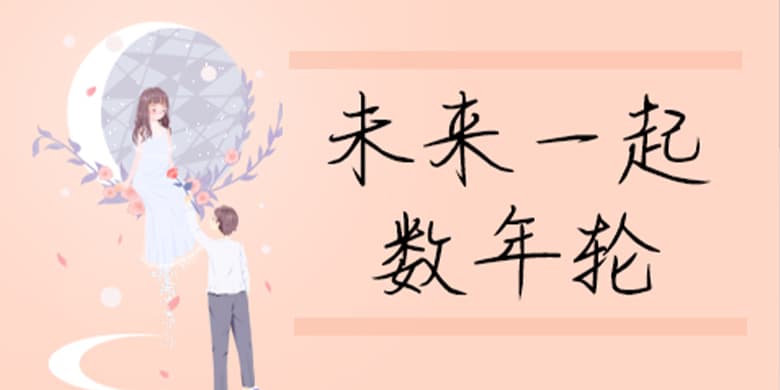
品牌:方正手迹设计师:王航发行时间:2020字库编码:简繁扩展(GBK)分类:常规书写·硬笔字体属性:精品字
未来一起数年轮是一款具有古典气质的的手写体。该字体中共收紧,外围笔画舒展延伸,笔画流畅连贯,笔锋锐利,转折直接。该字体适用于文艺类的书刊、品牌广告和产品包装设计,以及社交网络的个性化用字。